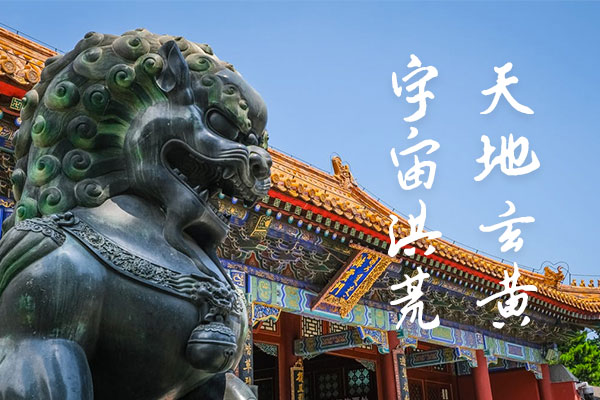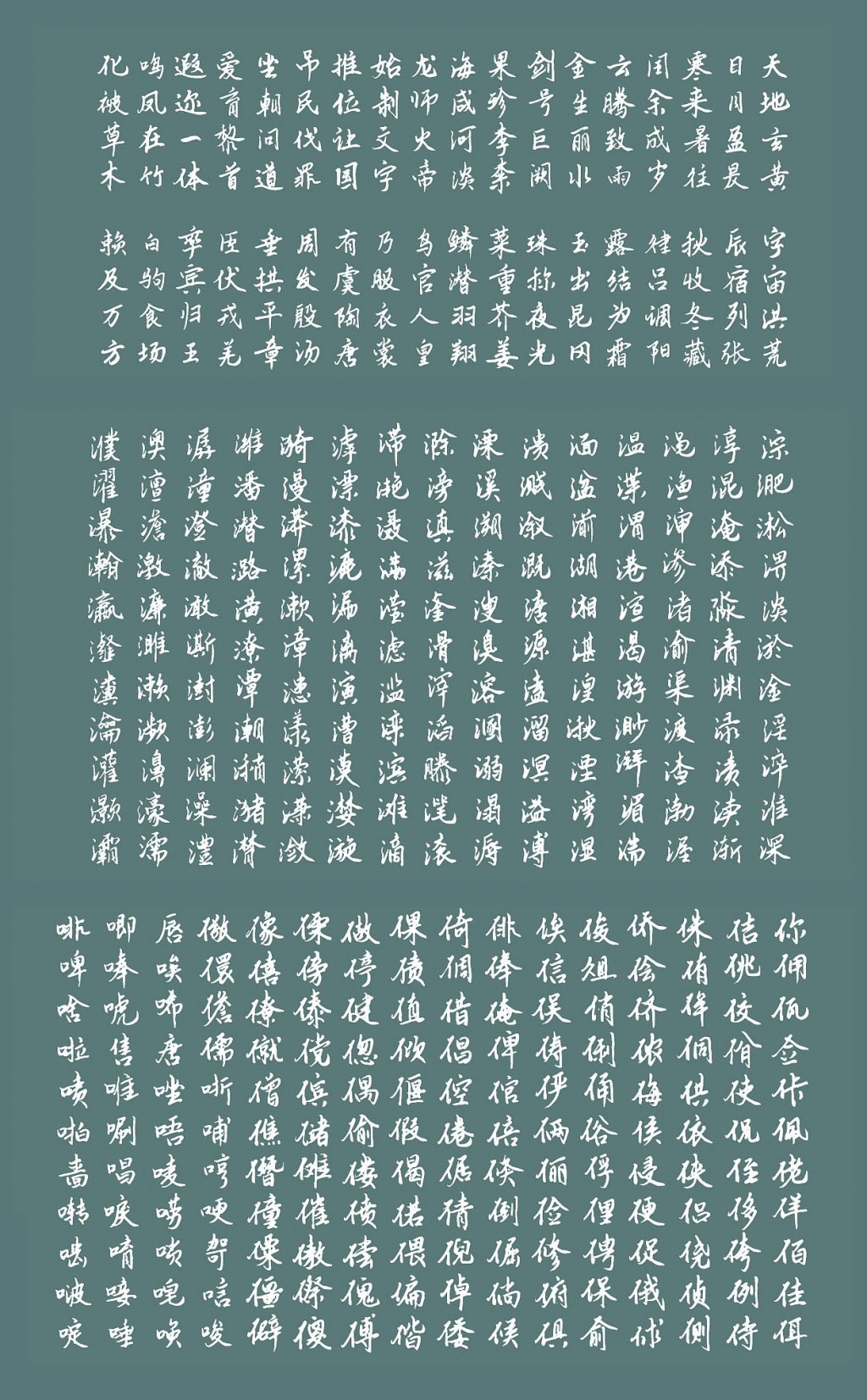
云峰静龙行书
云峰静龙行书是云峰字库新推出的首款免费商用字库,其行书字体风格独特,平稳流动,给人以强烈的视觉冲击力。
云峰静龙行书在设计中将复杂的笔画进行了简化和省略,使得字体更加流畅自然。同时,点画之间的呼应通过勾、挑、牵丝等手法得以加强,使得整个字形更加生动有力。此外,该字体还采用了圆转的笔画代替了方折的笔画,使得字体更加柔和自然,更具艺术感。